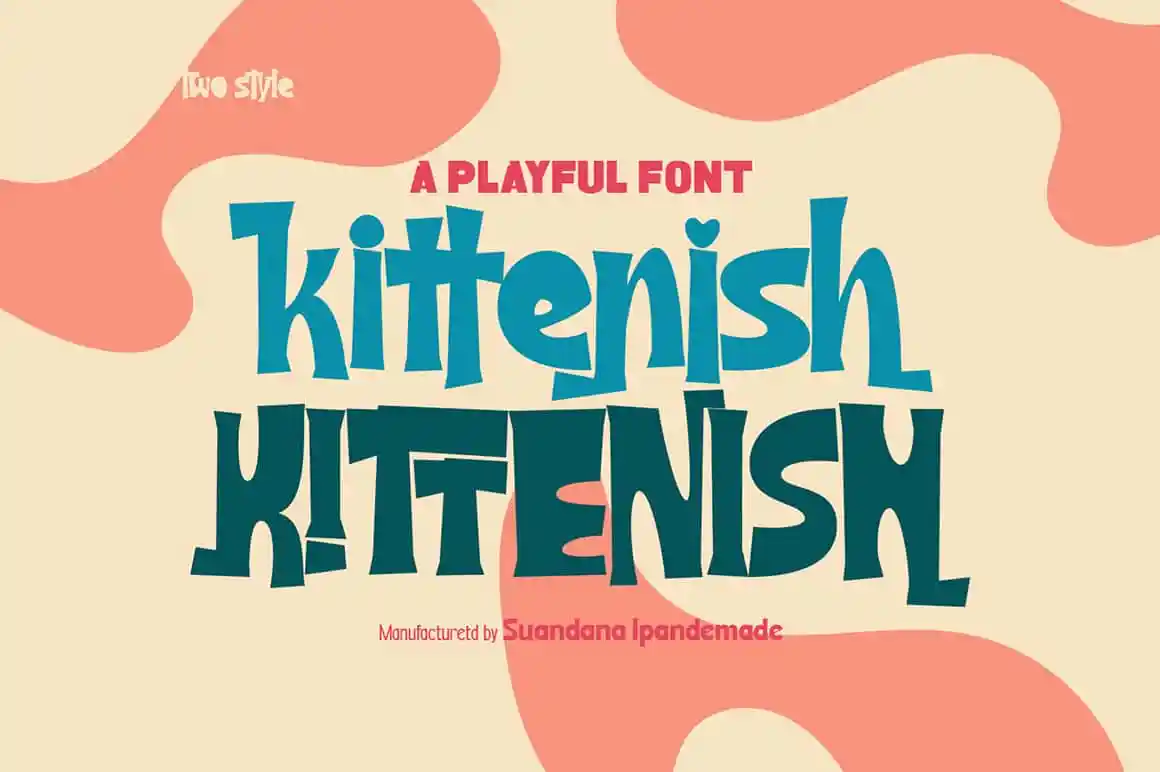
Kittenish Playful Font – Download Grátis
A fonte ‘Kittenish Playful Font’ é uma escolha ideal para quem busca dar um toque animado e original a qualquer projeto visual. Desenvolvida pela designer madeDeduk, essa fonte tem uma personalidade brincalhona que se destaca especialmente nas áreas de design gráfico, como livros, identidades de marca, embalagens de produtos, convites, citações, camisetas, rótulos, cartazes e logotipos. Ela é perfeita para criar um ar descontraído e empolgante em projetos variados, tornando-a uma fonte versátil que se adapta bem a diversos estilos de design. Seja na web ou impressa, a ‘Kittenish Playful Font’ trará aquele toque único e divertido que você está procurando para seus materiais.